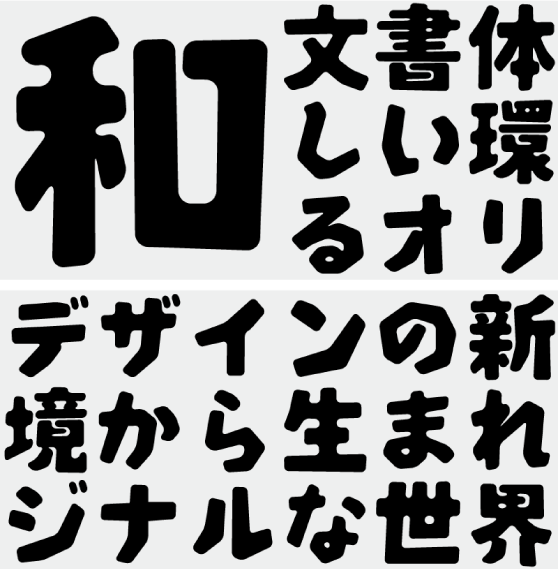
F1000-昭和丸 F1 Regular (Masahiko Yamada)
F1000-昭和のファミリーで、カドの取れたおっとりゴシック。
フォントの制作はJISの約7,000字が基準となっている。しかし、全てのフォントに本当にそれだけの字種が必要なのか。写植の時代にもそれよりはるかに少ない文字数で対応してきた筈ではないか。少ない文字数ですむのならばもっと多くのデザイナーがタイプフェイスのデザインに参加できる。そこから創意溢れるタイプフェイスが創作されることにならないか。そんな素朴な思いからFONT1000の活動は始まりました。
当初は日本語の文章に最低限必要な文字として漢字1,000文字+両仮名と若干の約物が選定されましたが、現在ではさらに人名漢字などを加えた漢字2,286文字+両仮名と約物、そしてアルファベットの収録が基本となっています (※F1シリーズは旧仕様:漢字1,000文字+両仮名・約物198文字のまま) 。
現在30名以上のデザイナーが参画、個性あふれる100書体以上のラインナップです。